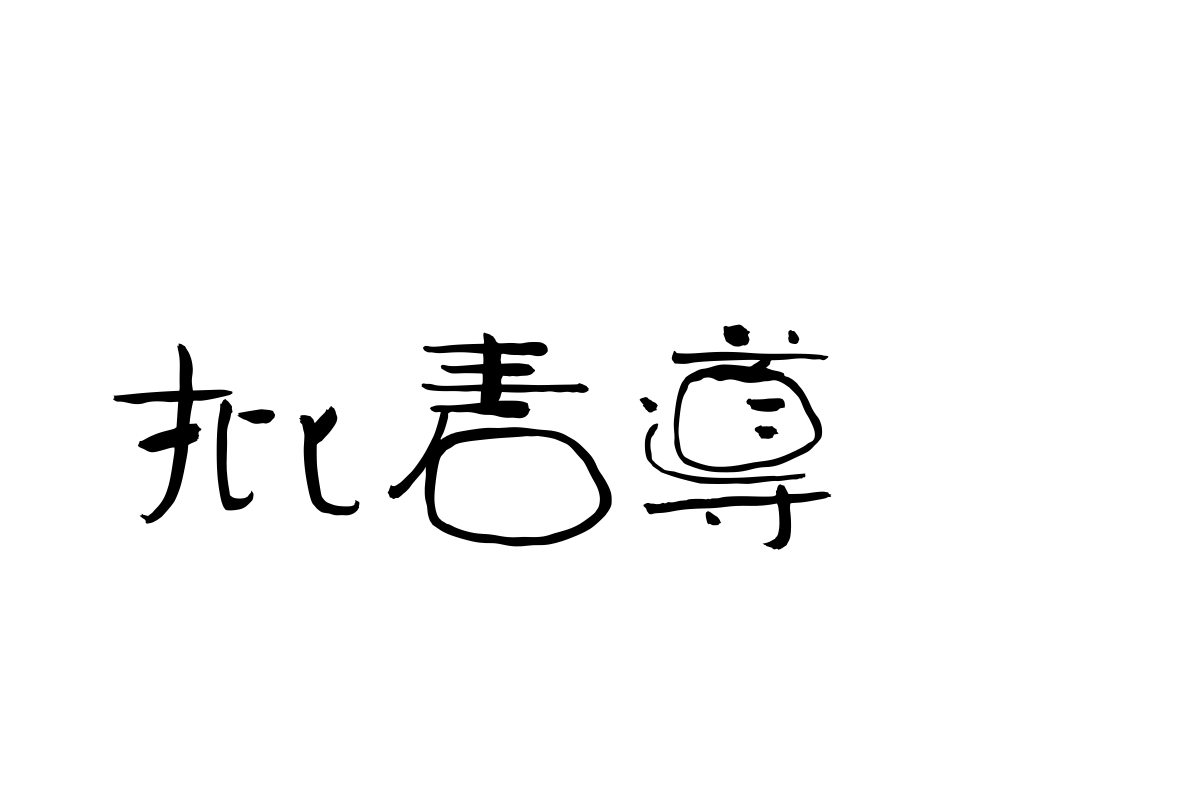
汉仪迪升夏日体是一款具有现代感和活力的字体,适用于夏季主题的设计。这款字体的特点如下:
1. 字形设计独特,线条流畅,给人一种清爽、舒适的感觉。
2. 笔画粗细适中,既有力度又不失柔和,适合用于各种文字设计。
3. 字体结构紧凑,易于阅读,适合用于标题、正文等需要突出重点的场合。
4. 色彩搭配鲜明,与夏季主题相得益彰,能够吸引人们的注意力。
5. 适用范围广泛,适用于广告、海报、杂志、网站等各种媒体平台。